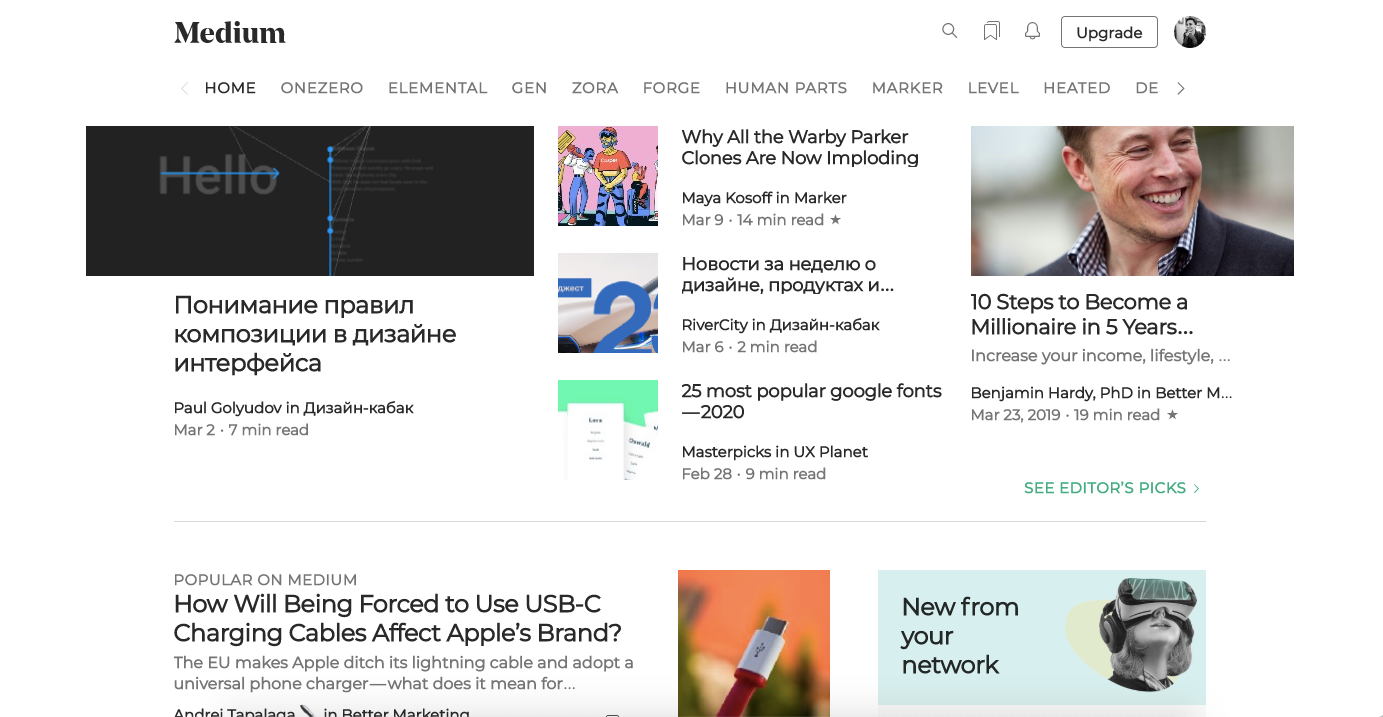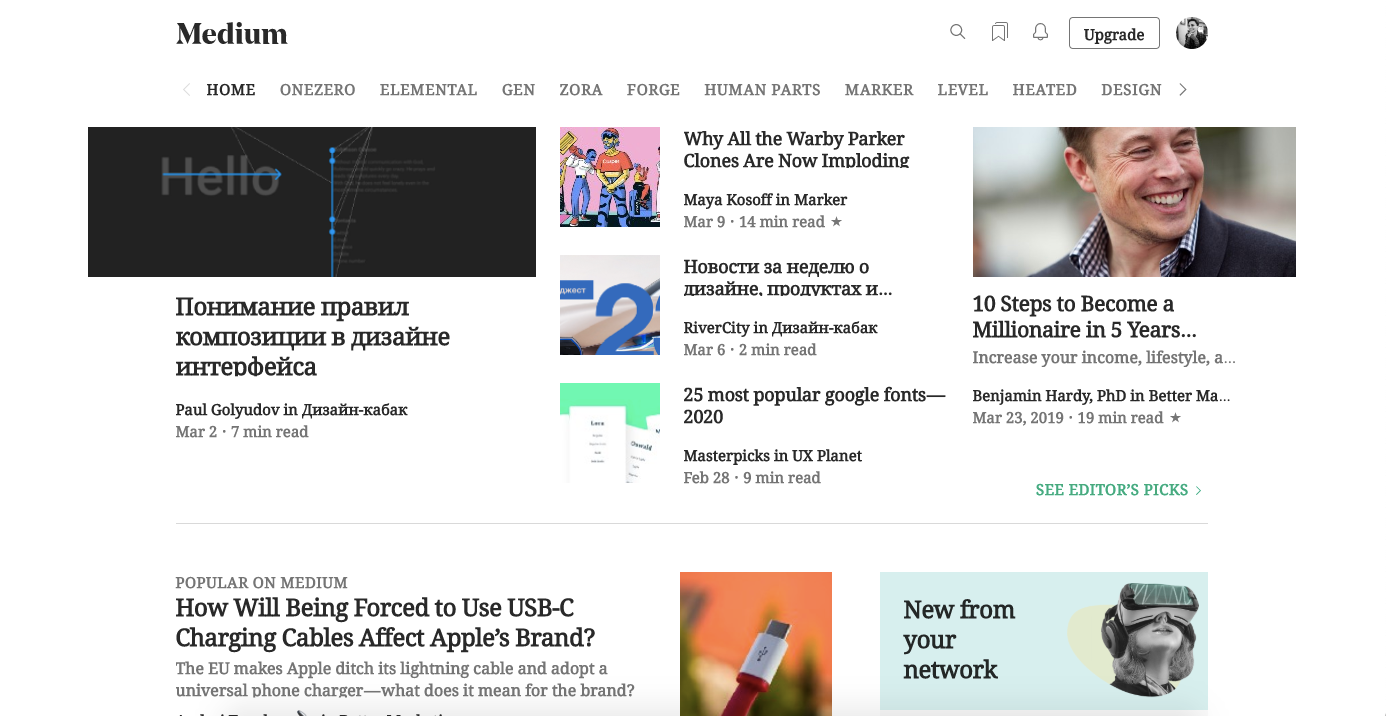
Как в проекте привести шрифты в порядок, если в нем сплошной беспорядок. Наш опыт
Недавно, мне были переданы для работы проекты, в которых надо было все упорядочить, привести к системе и освежить. Один проект уже был запущен и им пользовались реальные клиенты, поэтому здесь было важно не накосячить. Второй находился на стадии разработки и существовал только на деве.
Проблема
Проблема была в том, что в макетах не было никакой системы: отсутствовали компоненты/символы (Фигма/Скетч) для иконок и контролов, отсутствовали цветовые и шрифтовые стили, сеток тоже не было. В общем, бардак. И к тому же, используемый шрифт Poppins, был контрастным и в мелком кегле плохо читался и много брал на себя. Да и не нравился.
Чтобы просто примерить шрифт, необходимо было его менять в каждом месте на странице 🤯, при этом, конечно же, дизайн «поплывет». А затем повторить все сначала для нового пробного шрифта. Звучит совсем не оптимистично.
Решение
Но выход нашелся. Мы использовали расширение для хрома Font Changer, которое заменяет шрифт сайта сразу в браузере. И присматривались к шрифту сразу на реальном проекте.
Вот как можно «поиграться» со шрифтами Медиума:
Montserrat bold
Noto Serif
Последовательность действий
Механика по упорядочиваю шрифтов очень простая:
1. Находим варианты шрифтов на Google Fonts, к примеру.
2. Примеряем их к сайту с помощью расширения. Причем можем посмотреть сразу в разных кеглях и жирности. Выбираем оптимальный.
3. Описываем стили и назначаем их в Фигме.
4. Начинаем работать с разработчиком в паре. Сначала просто заменяем шрифт на сайте и не трогаем размеры и жирность. В итоге в браузере что-то выглядит хорошо, что-то мелко или крупно, но в целом, ничего не ломается.
5. Теперь девелопер описывает у себя стили для текста и межстрочных интервалов.
6. А мы приводим макеты в порядок страницу за страницей. И отдаем их постепенно разработчику на верстку.
7. И также постранично внедряем изменения на сайте. Так «причесываются» заголовки, настраиваются стили таблиц, фиксируются компоненты, стили поп-апов и т.д.
После этой работы можно уже менять шрифт одним нажатием кнопки и проводить редизайны.